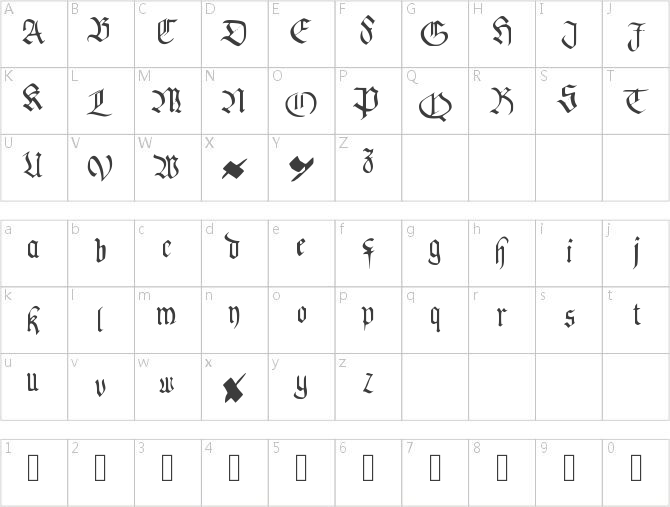
PentaGram’s-Callygraphy
PentaGram’s-Callygraphy介紹
PentaGram’s-Callygraphy字體字庫是一款讓人賞心悅目、百看不厭的英文字體,適合各類廣告和產品包裝設計應用,字體大小0.02MB,格式為ttf字體,上傳用戶是漫步云端,作者/版權方為未知